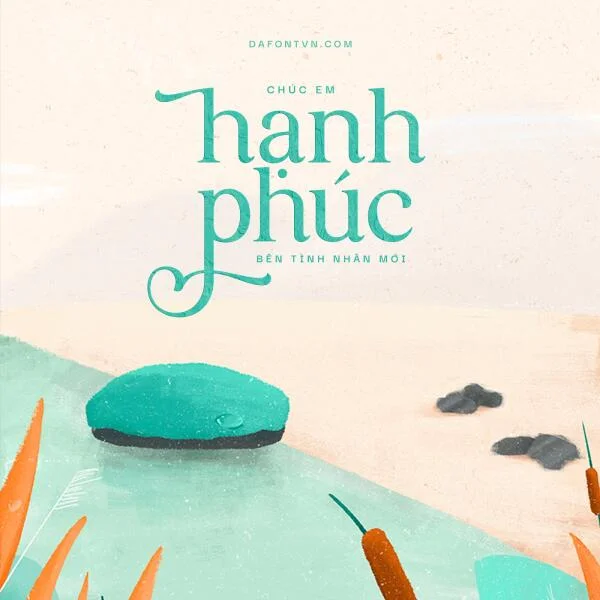
Tải Font Kingdom Việt hóa ấn tượng cho mọi bài thiết kế
Trong bài viết này, IoTStartUp sẽ giới thiệu đến các bạn 1 chiếc font việt hóa mới được ra mắt mang tên Kingdom - Một kiểu font ấn tượng, hiện đại và rất độc đáo. Tải về ở cuối bài viết!
Tổng quan về Font Kingdom Việt hóa
Font Kingdom mang đến cho bạn những điểm nhấn ấn tượng bởi nó đi kèm với rất nhiều glyph đẹp cho cả chữ hoa và chữ thường vì vậy bạn có thể thỏa sức sáng tạo để có thể tạo ra nhiều thiết kế ấn tượng hơn. Đây là một font chữ cực kì độc đáo và đem lại ần tượng mạnh, khó quên cho người dùng nhiều trải nghiệm mới..
Font việt hóa Kingdom Preview 1
Mẫu 1
Font việt hóa Kingdom Preview 2
Mẫu 2
Font việt hóa Kingdom Preview 3
Mẫu 3
Chi tiết các ký tự của Font Kingdom Việt Hóa
Font việt hóa Kingdom Preview 4
Chi tiết ký tự 1
Font việt hóa Kingdom Preview 5
Chi tiết ký tự 2
Font việt hóa Kingdom Preview 6
Chi tiết ký tự 3